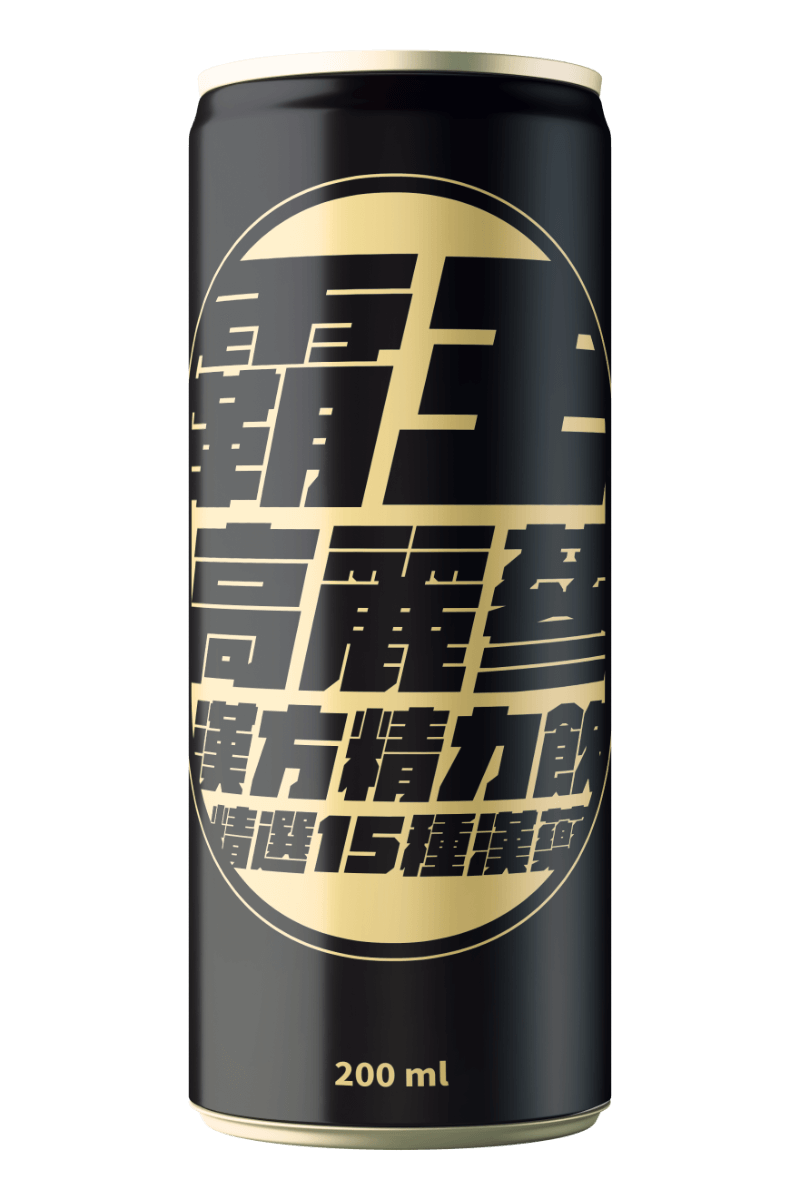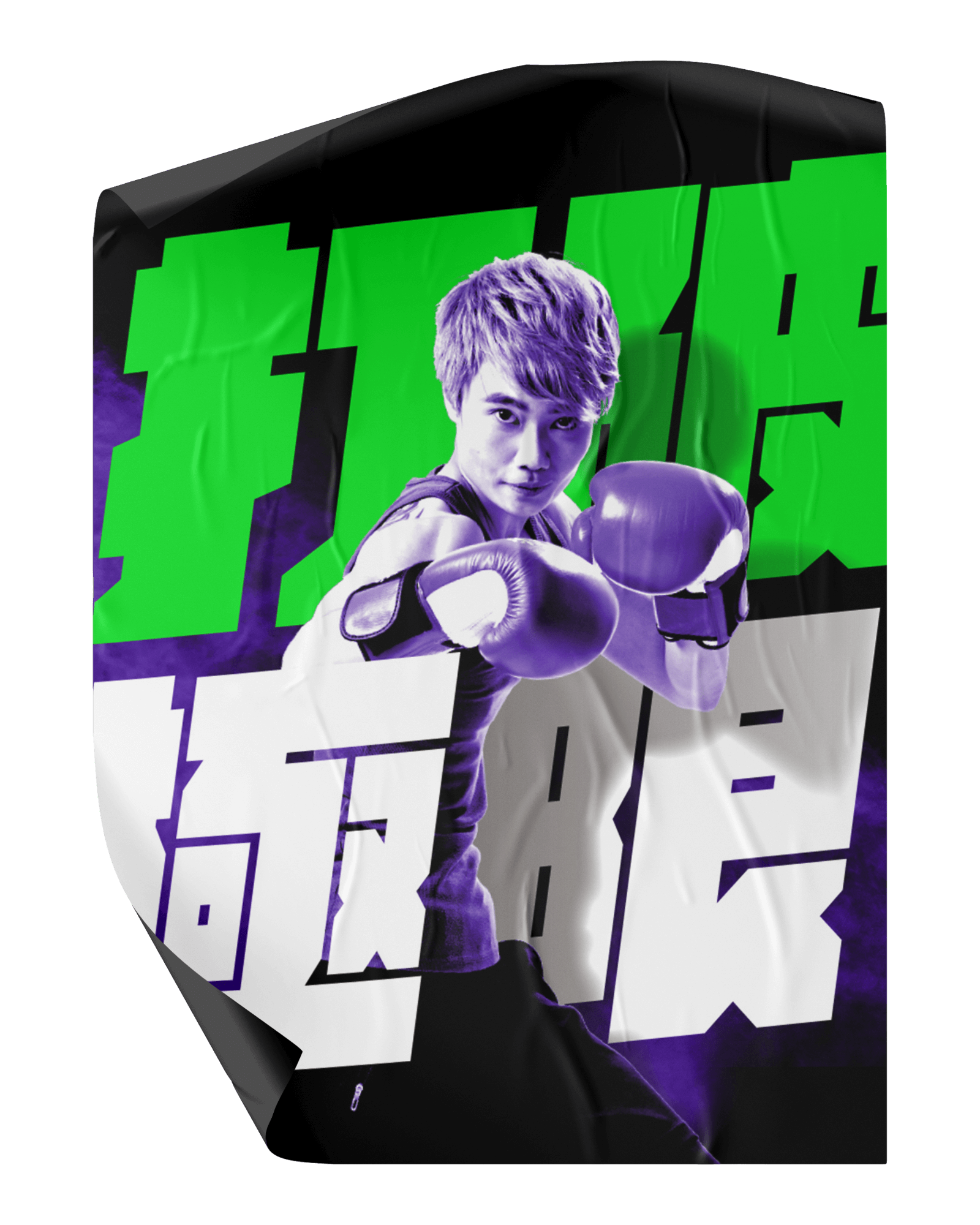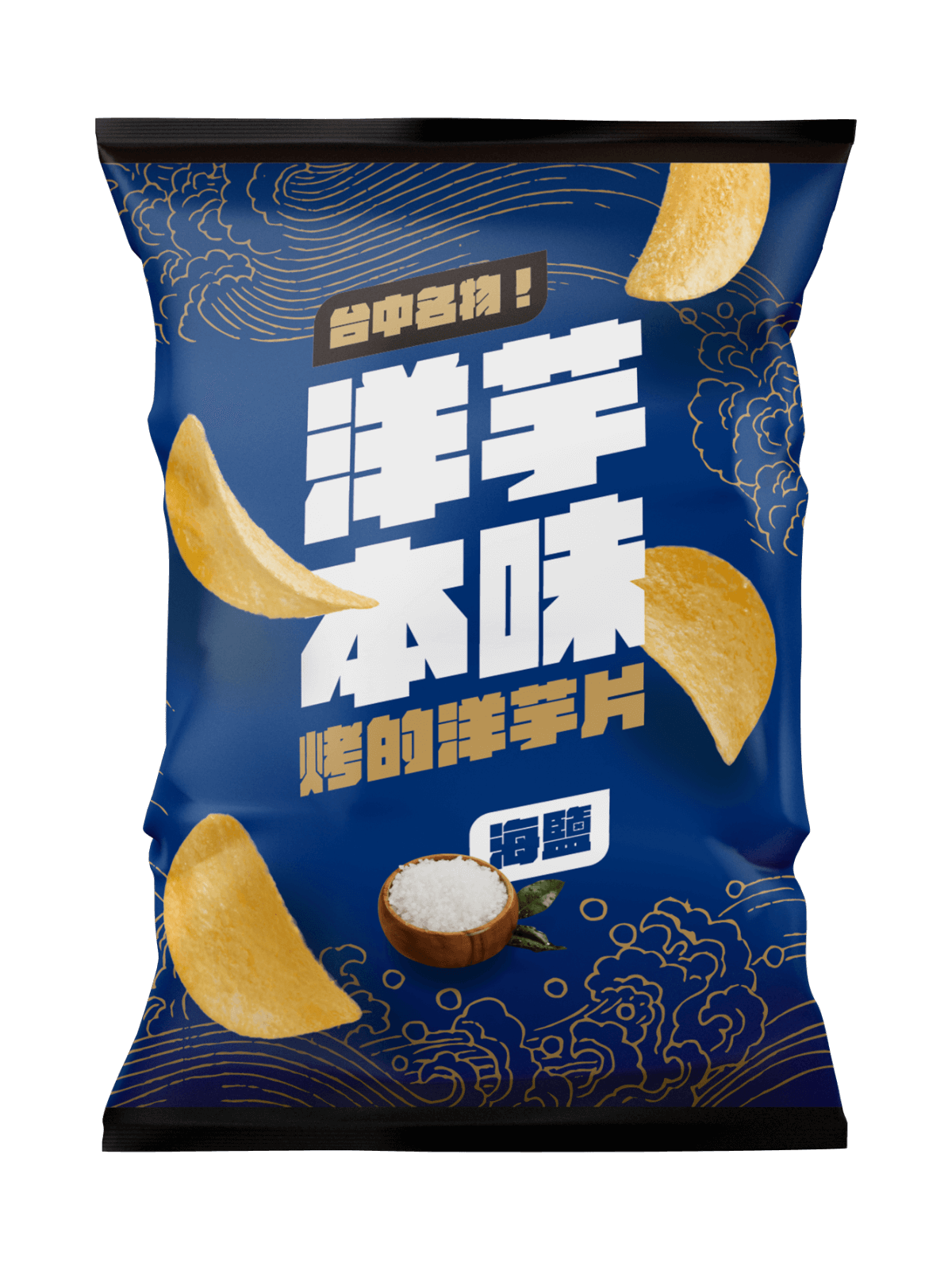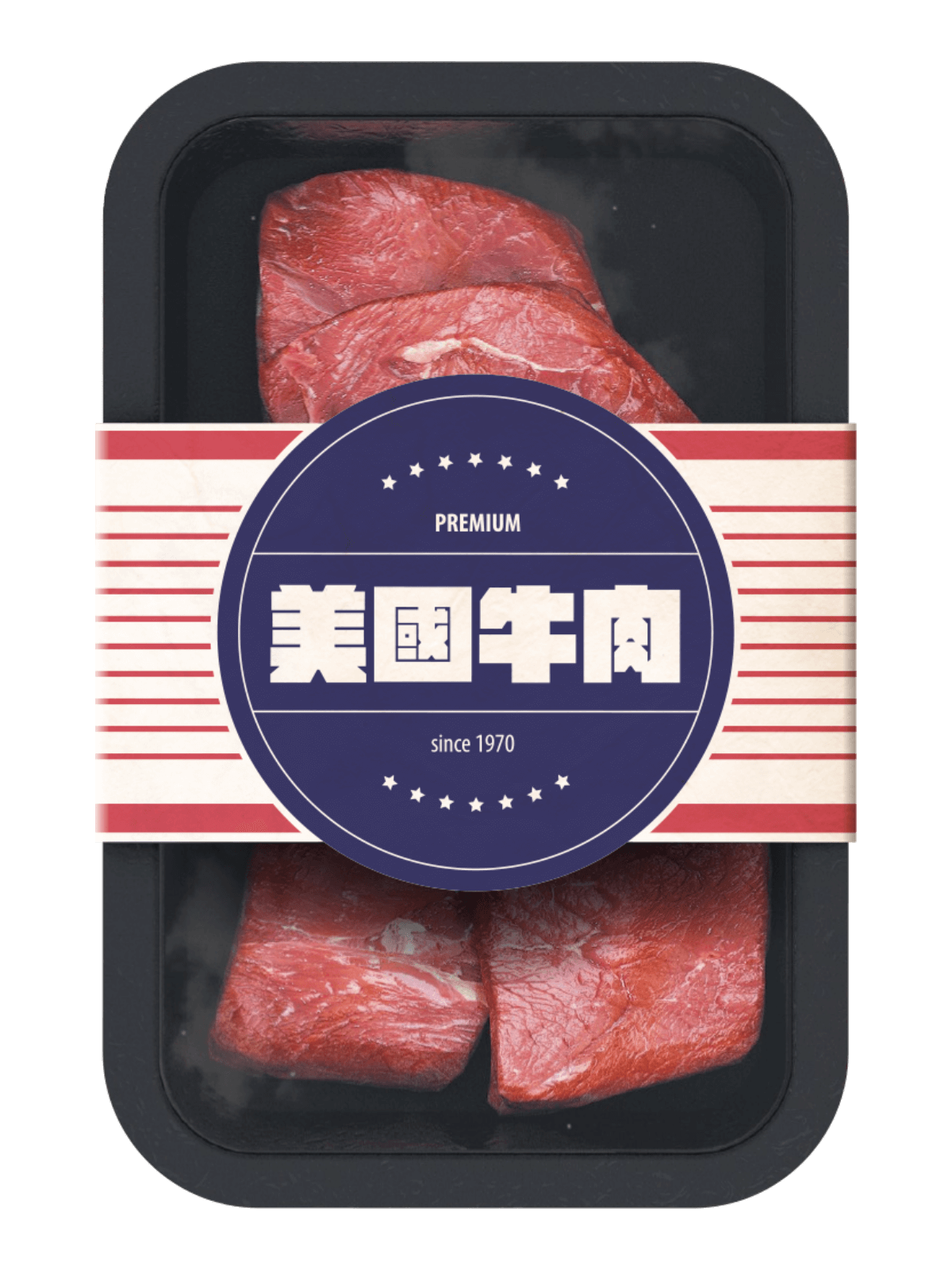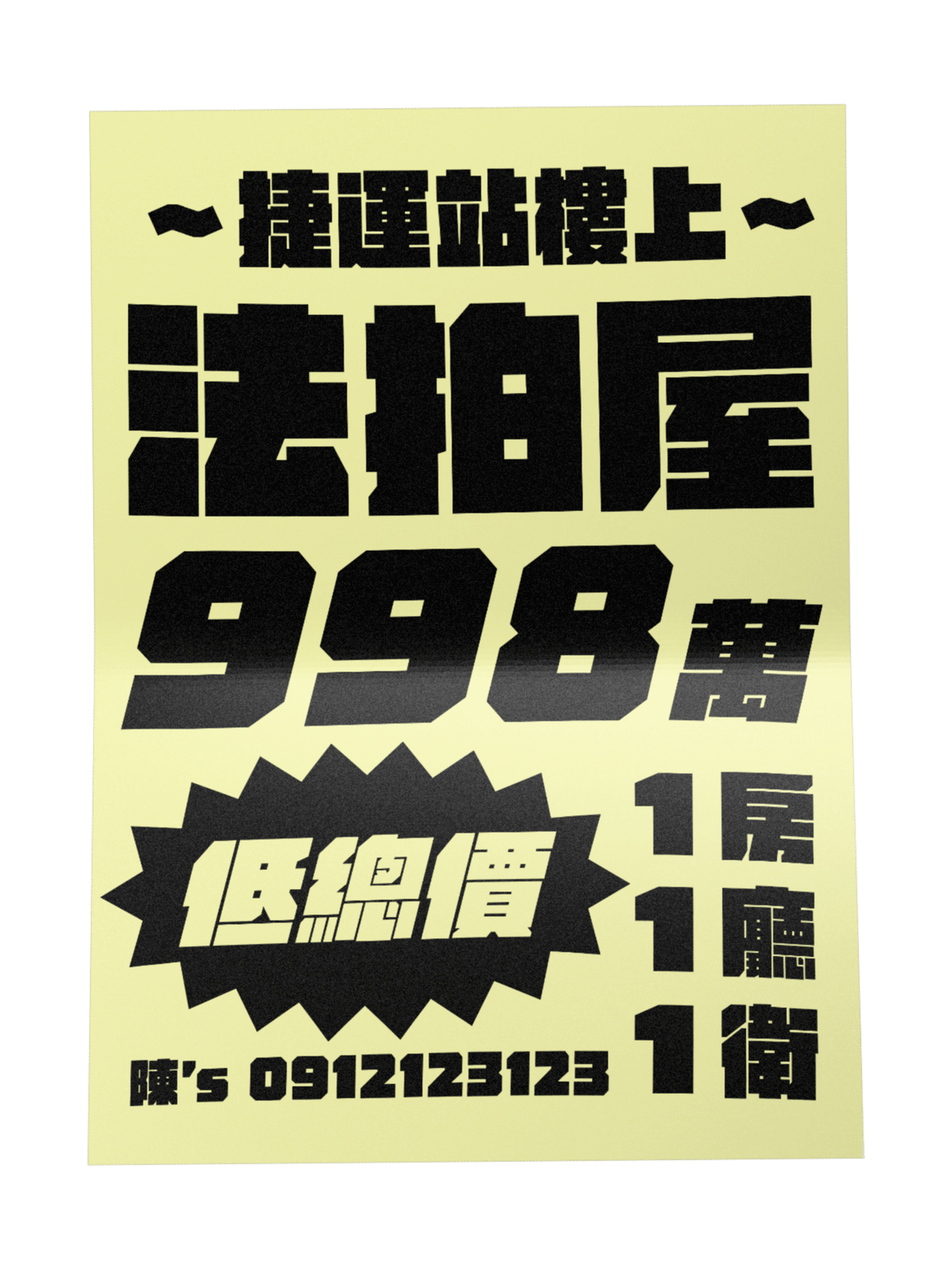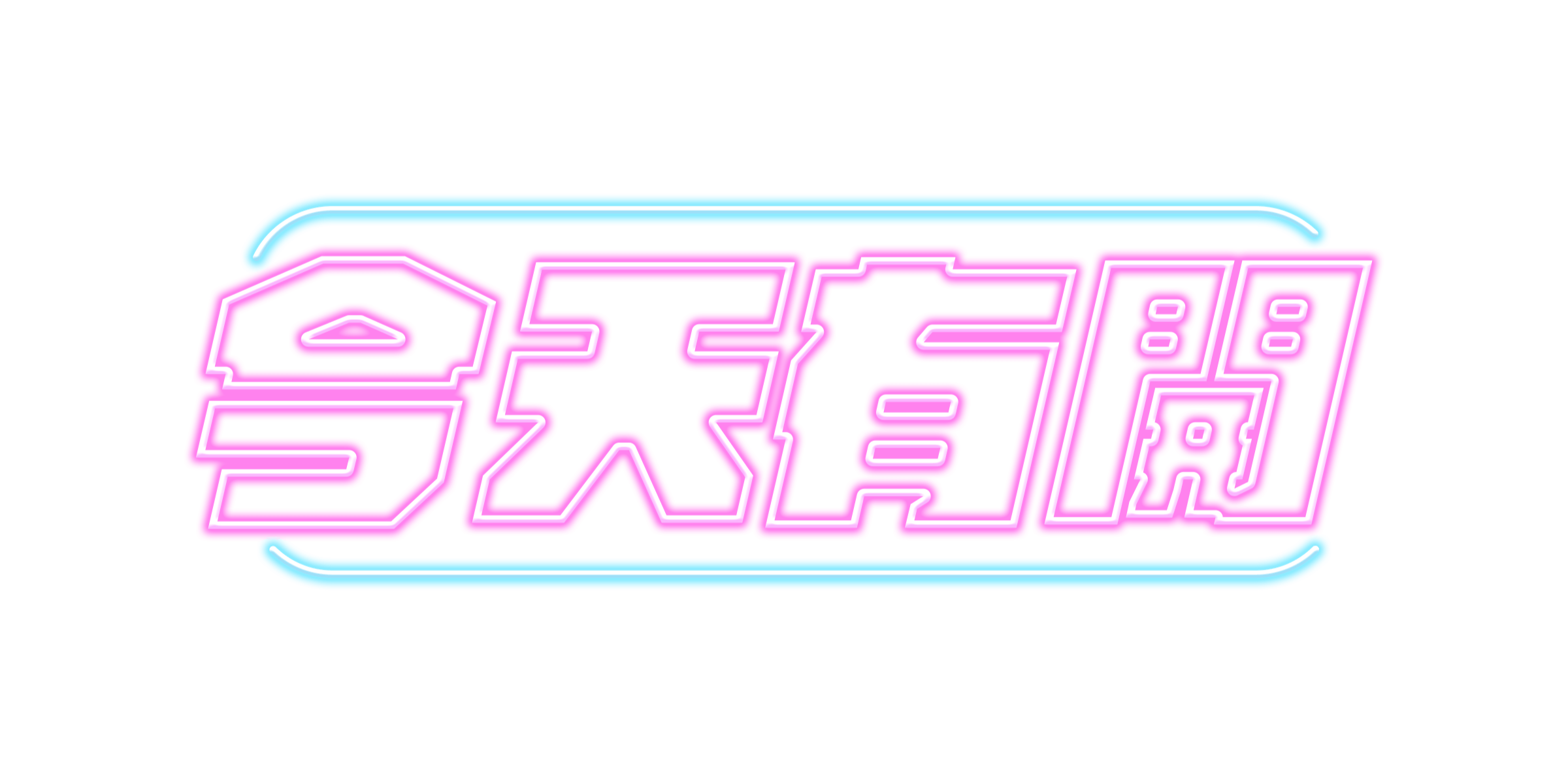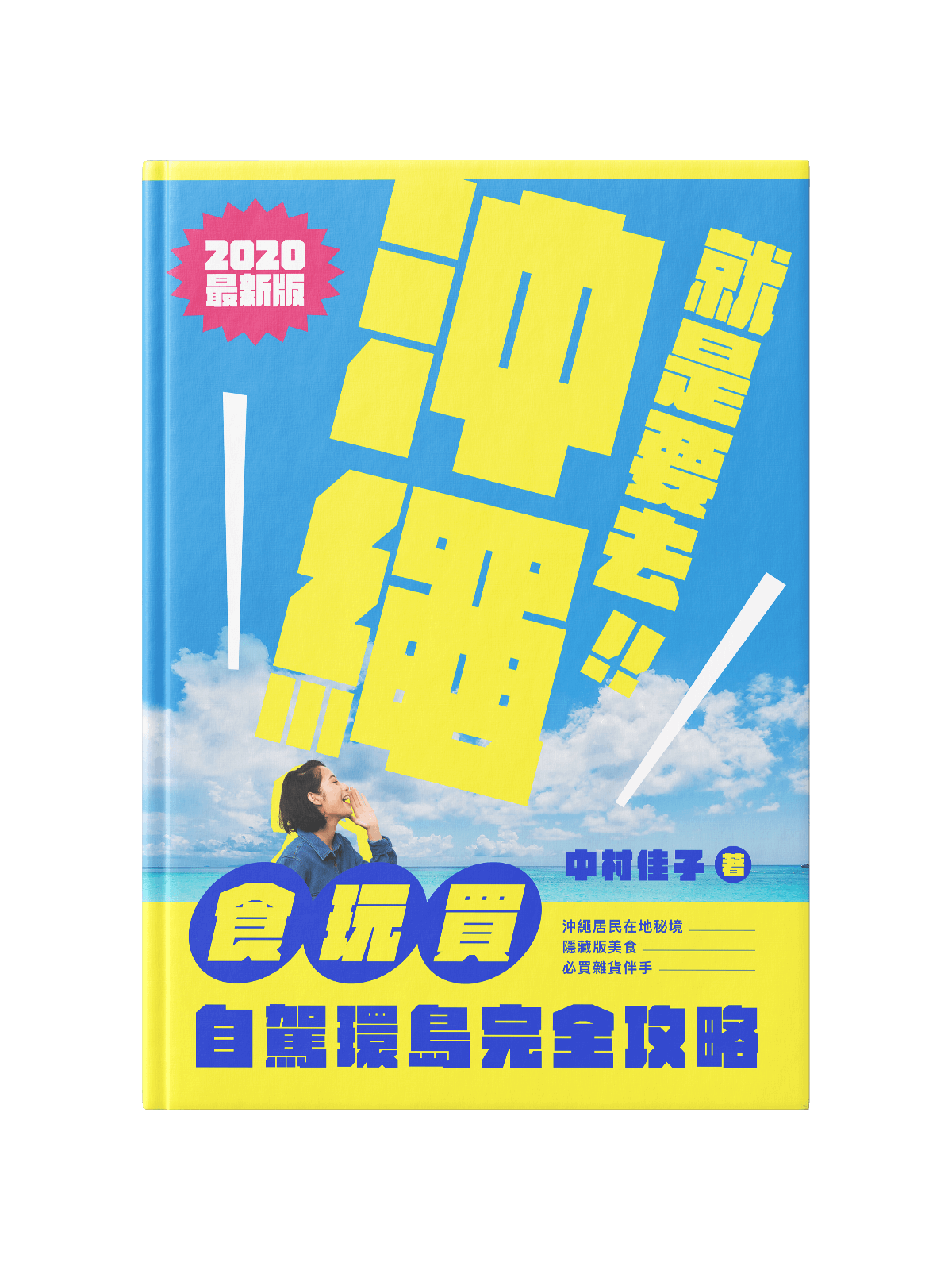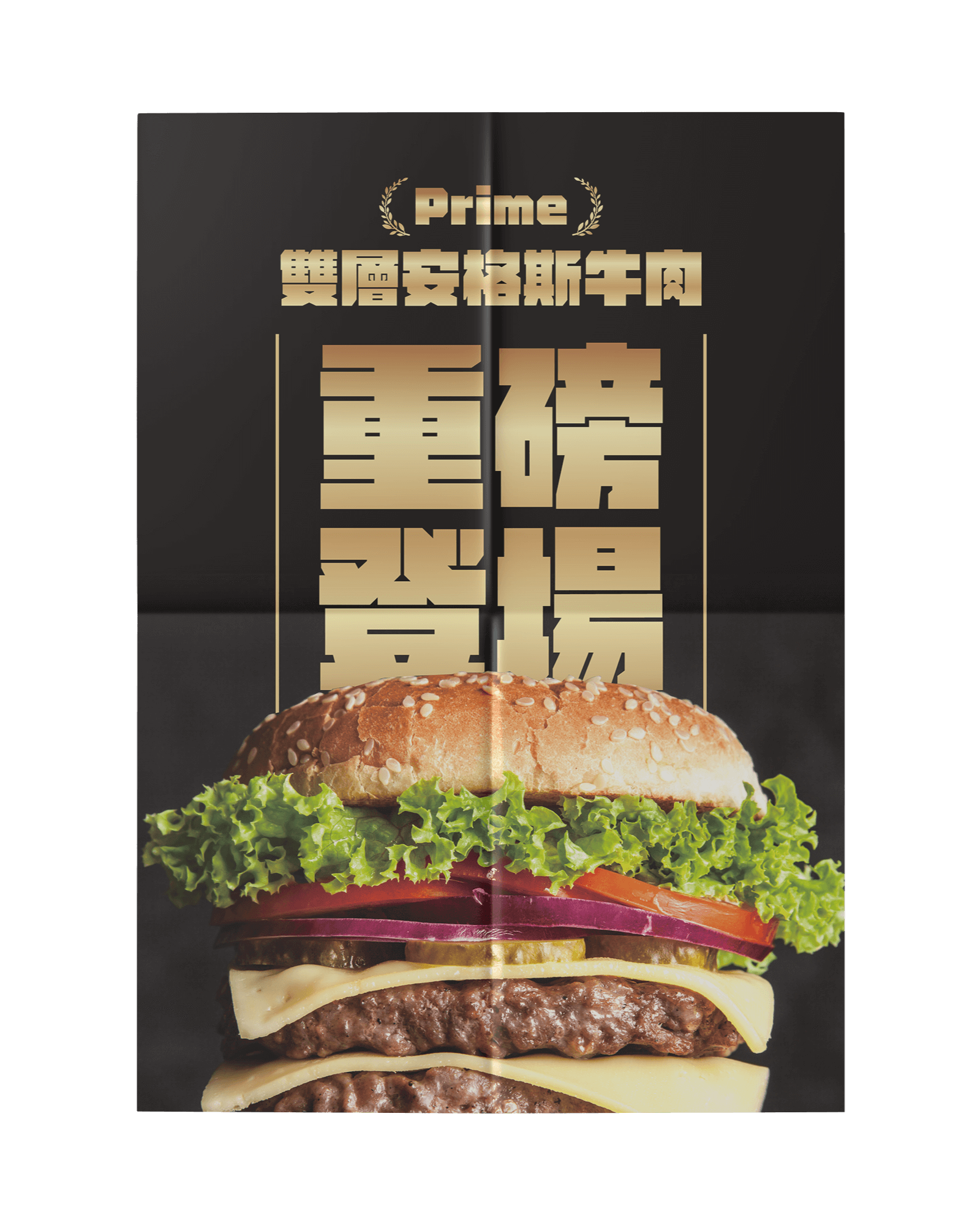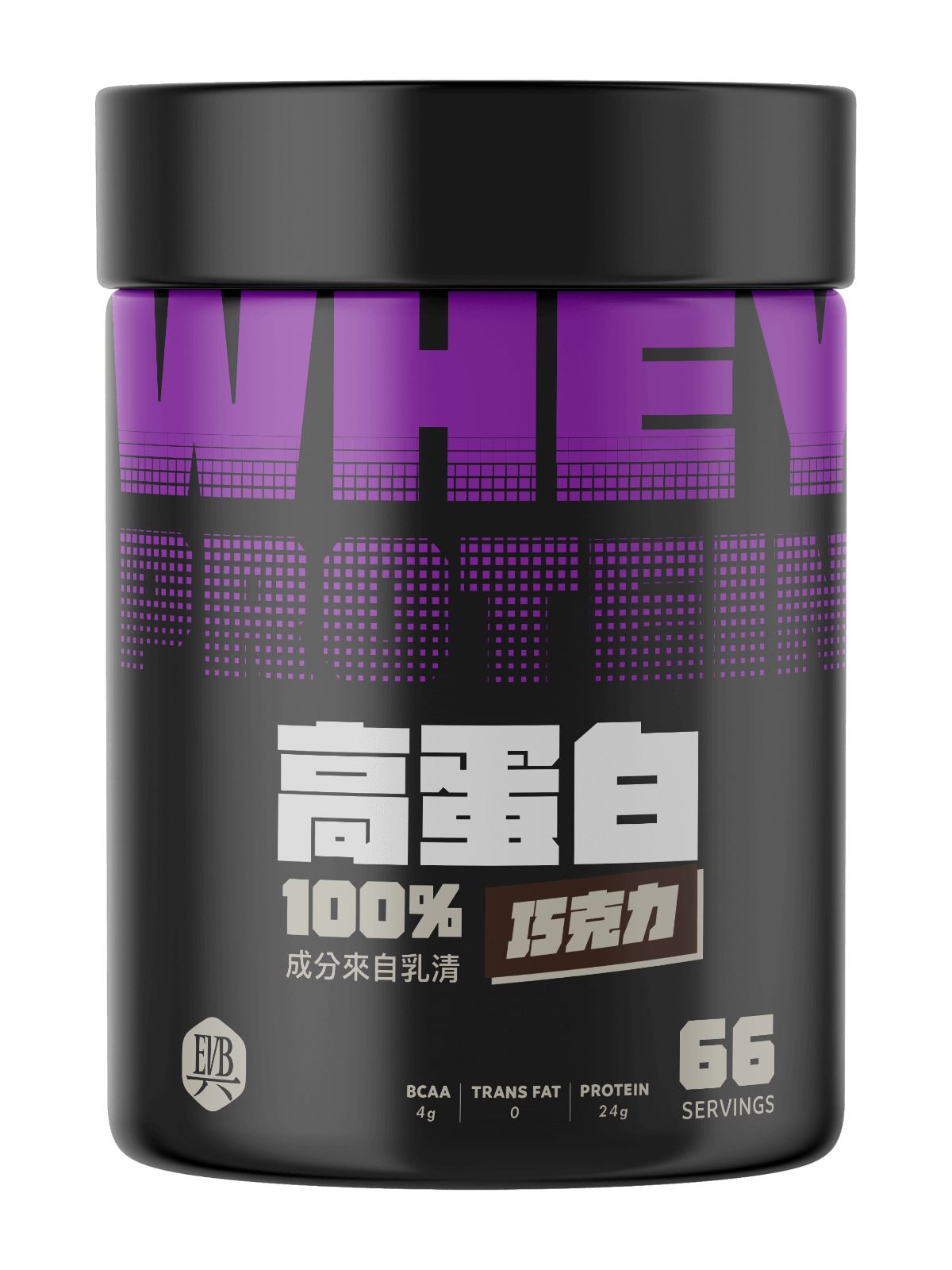
激燃體
全滿爆發,威力無比!
充滿張力的設計,讓你的
貼文、影片、包裝、海報無法忽視。
正
體
斜體
隆重
上市
宇宙最粗
粗到生火
設計師林芳平以粗壯有力的骨肉、
傾斜的衝撞力道,
拉高字體的聲量。
激烈燃燒
極端的空間分配,帶來極致的視覺衝擊。
滿出來,衝出來,極端的字重很難清楚明白。
設計師林芳平施展視覺幻術,精簡造型,
大幅降低碎形的影響,使文字空間更明確。
狠,清楚
狠
激燃體的設計故事
拯救字太小、字太細、字不夠出來的危機,我們準備了超級武器
行銷 燃料
精雕細琢的訴求卻沒人理?
用心繪製的主視覺沒人在意?
問題在字體!
特價不等人?用激燃體為你的限時特賣做出急迫感;
假訊息太猖狂?用激燃體引起關注。
激烈燃燒的小宇宙,將震撼你的觀眾!